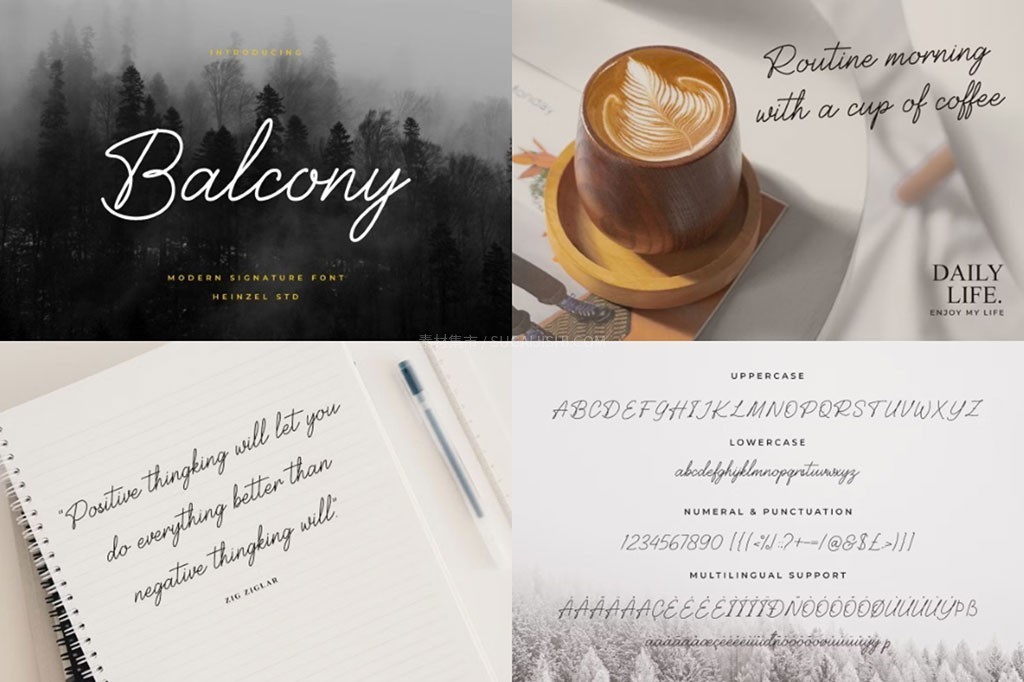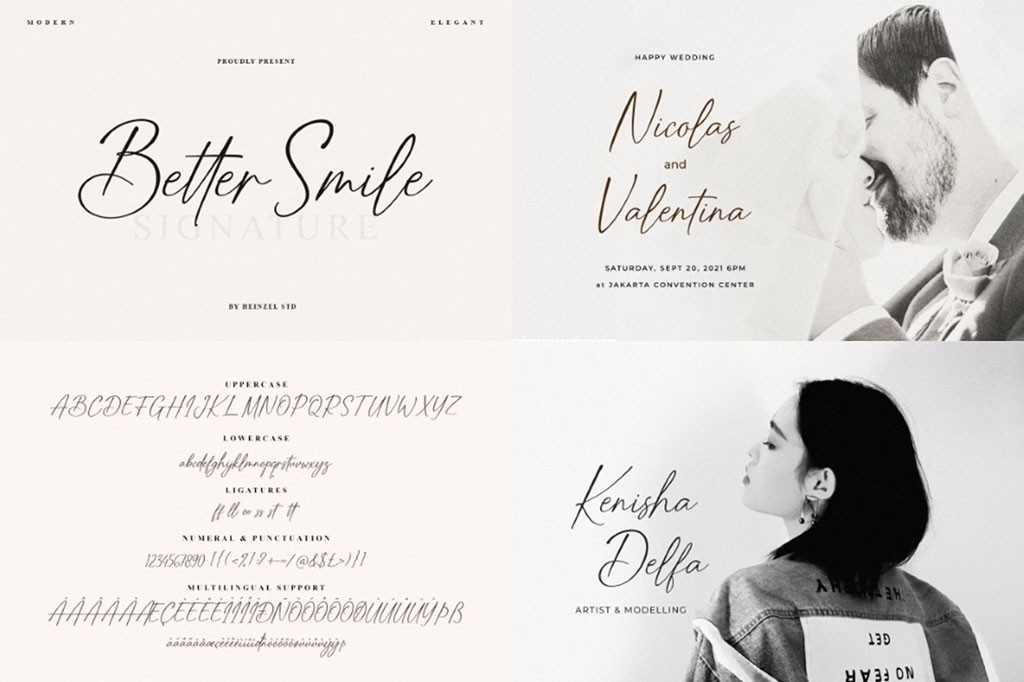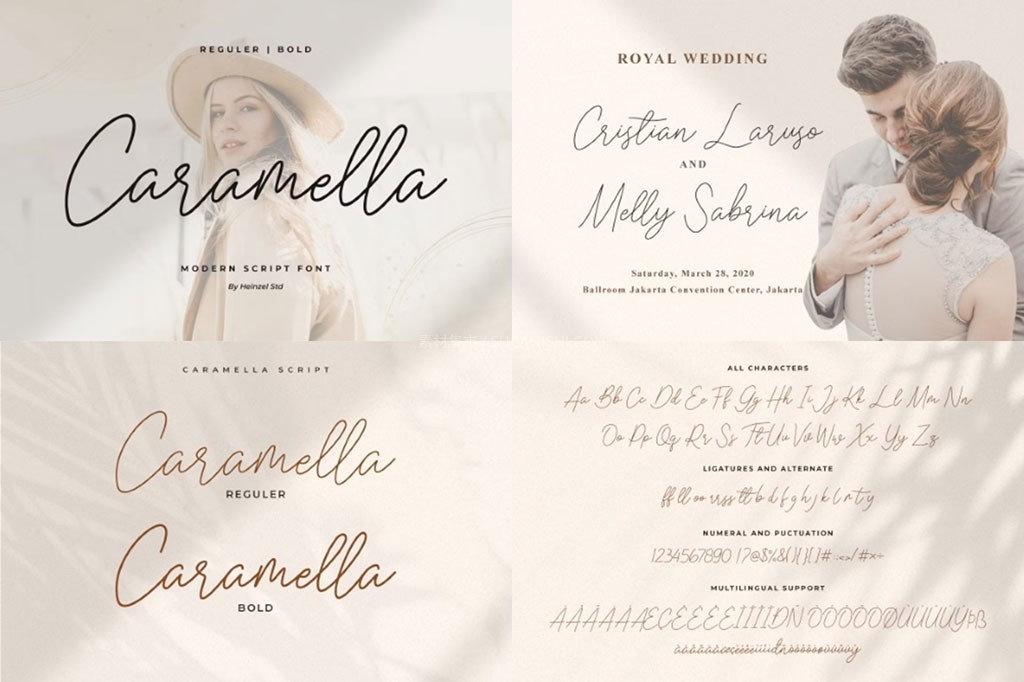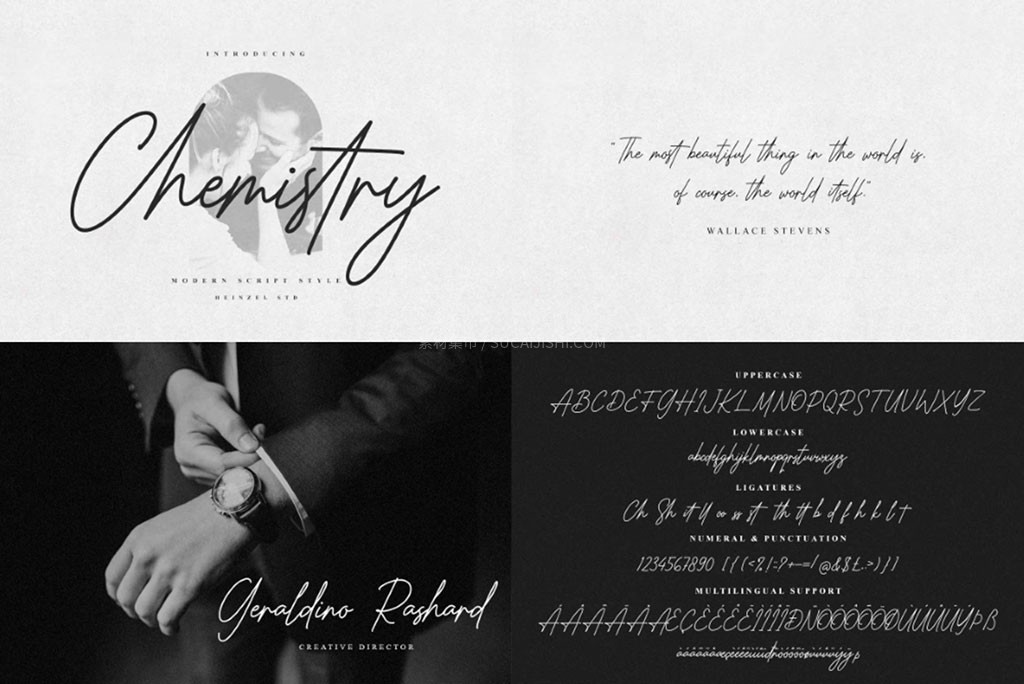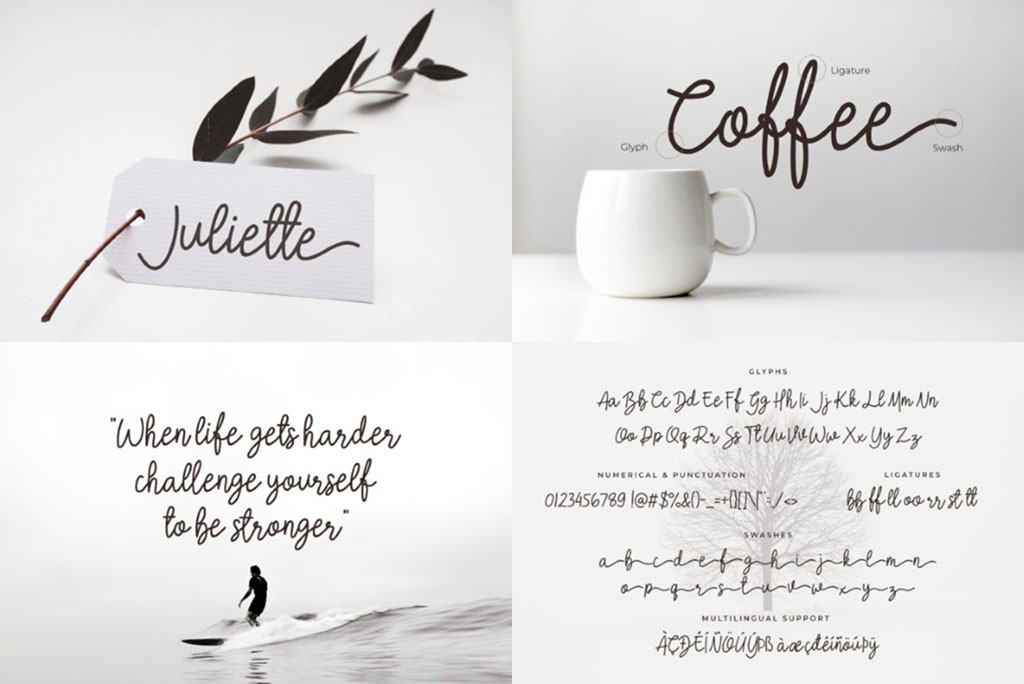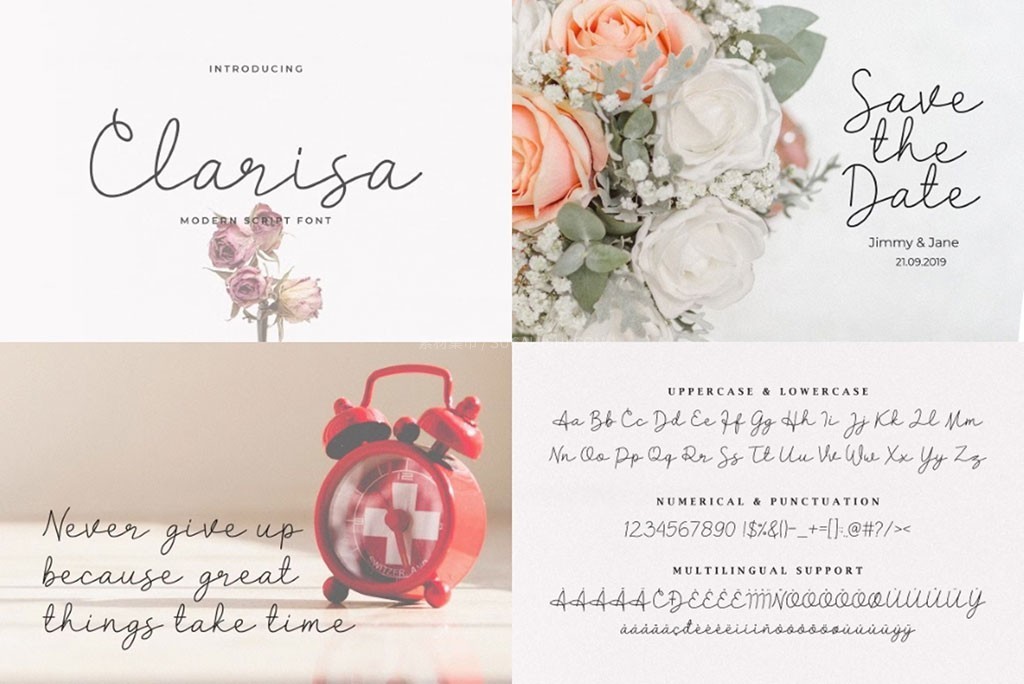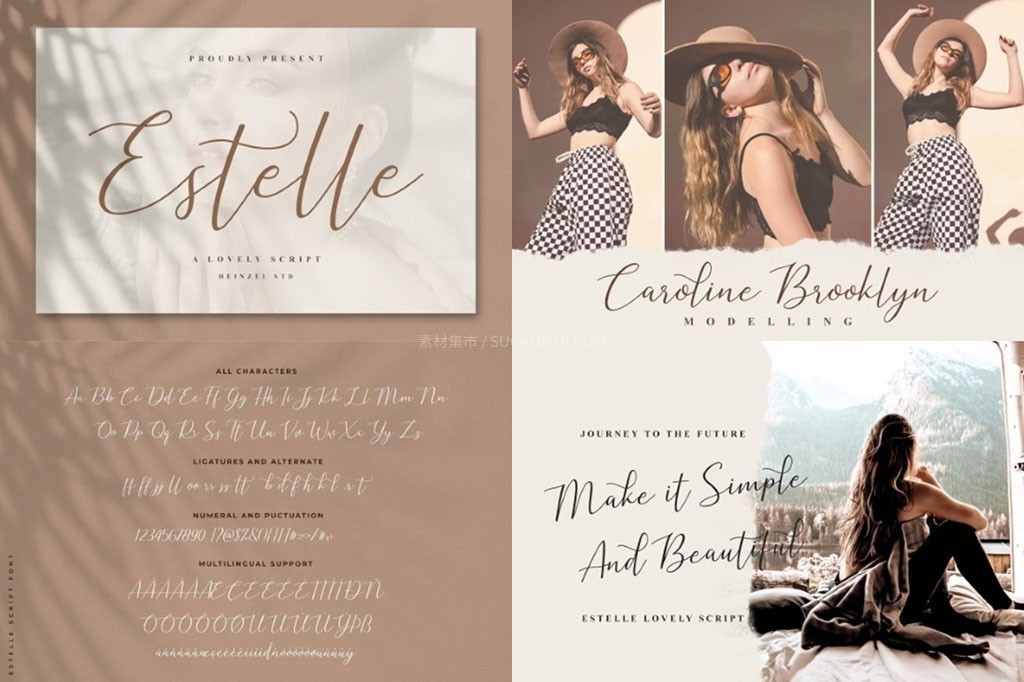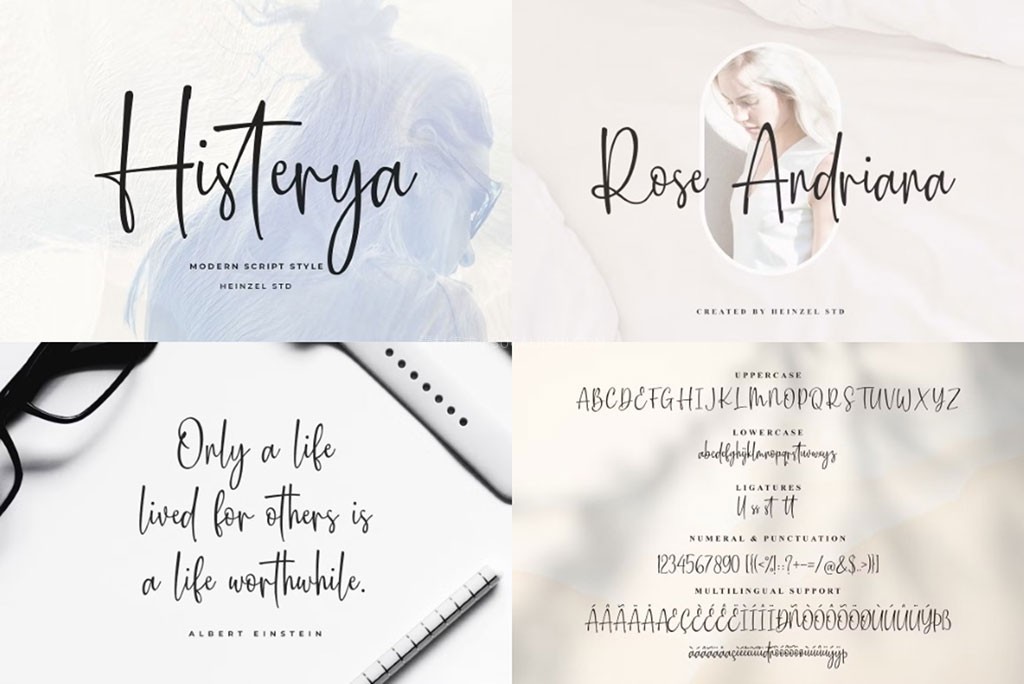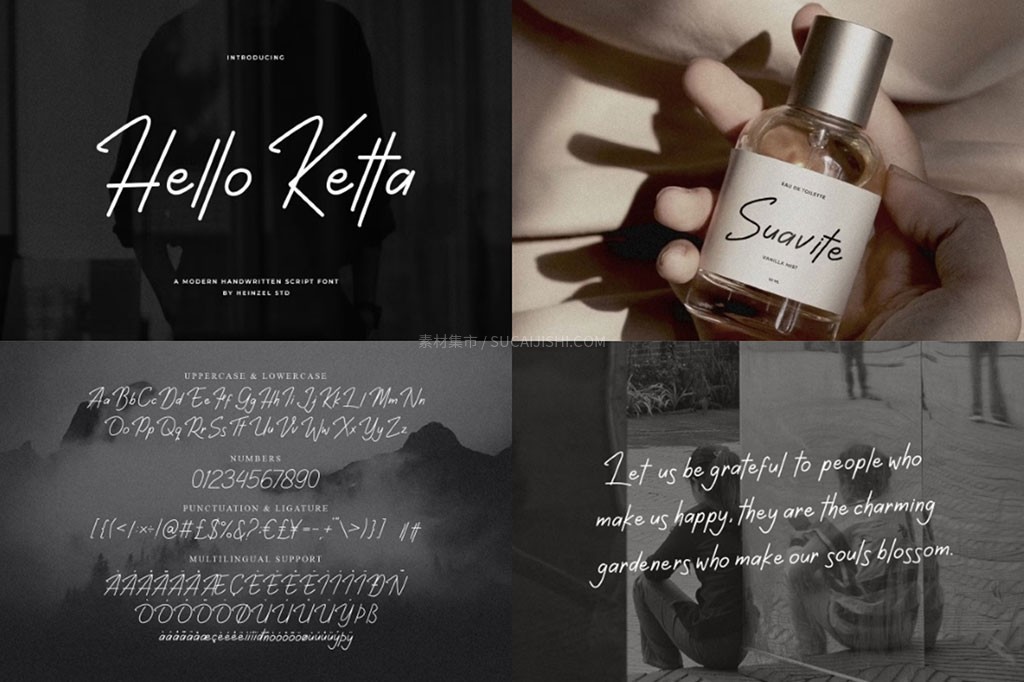
22款高级感现代手写英文字体
超级实用的“22款现代手写字体合集”!不管你是做品牌视觉,还是日常的排版设计,这套合集绝对能让你的作品瞬间拉满高级感。
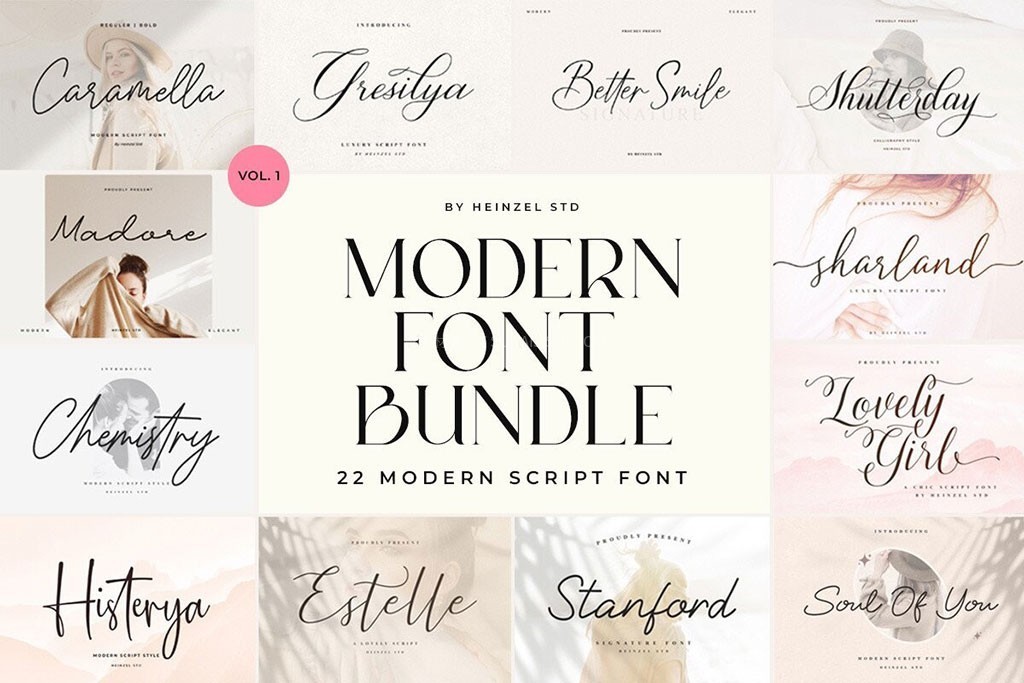
里面涵盖了多种手写风格,包括慵懒随性的签名体 (Signature Font,比如超有质感的 Silver City 和 Better Smile)、优雅的连笔书法 (Calligraphy Script)、以及极简的单线手写体 (Monoline Signature)。随手一打就是满满的艺术氛围感,不用再到处找字啦,一套直接搞定各种设计需求,赶紧马住用起来吧~22款高级感现代手写英文字体